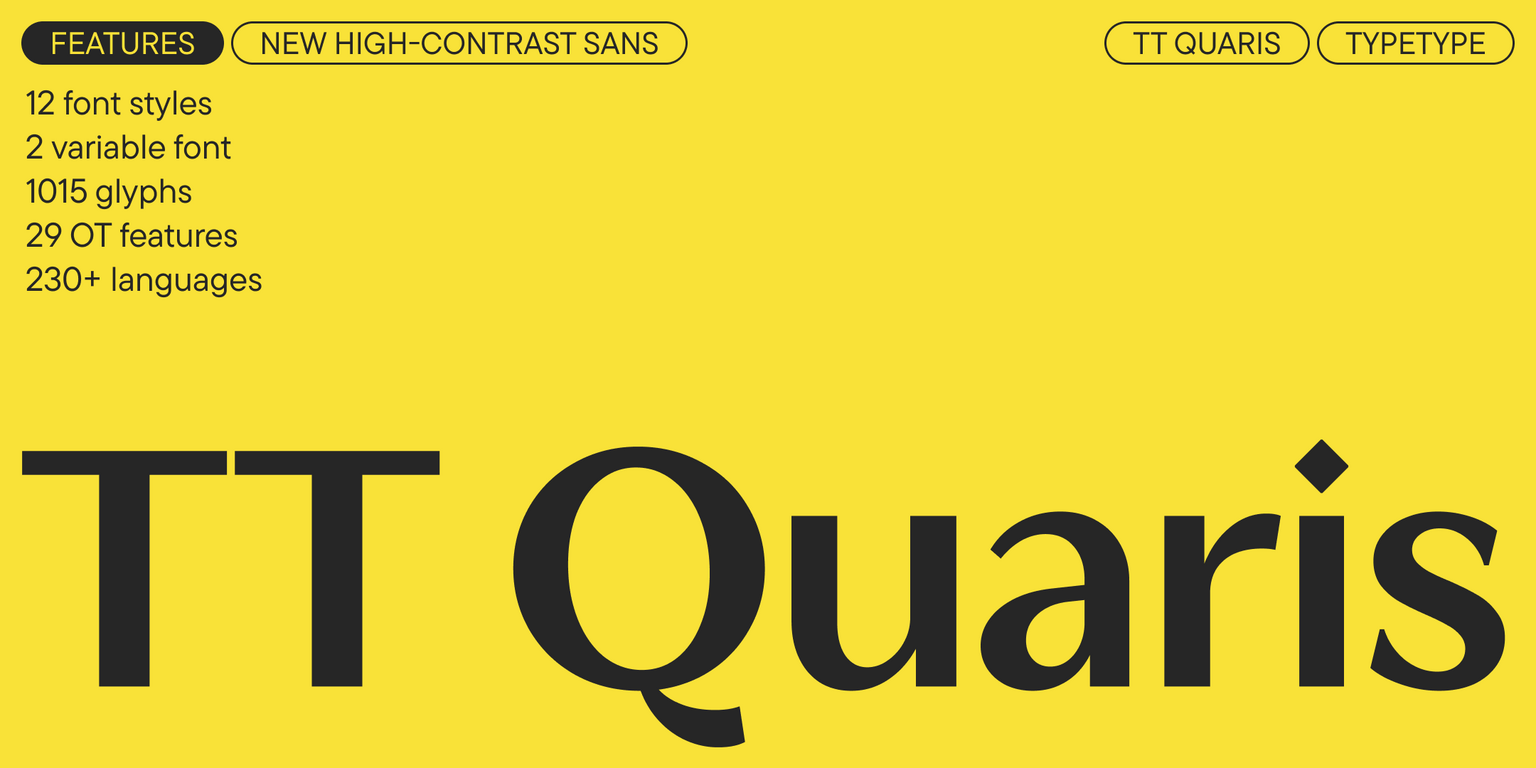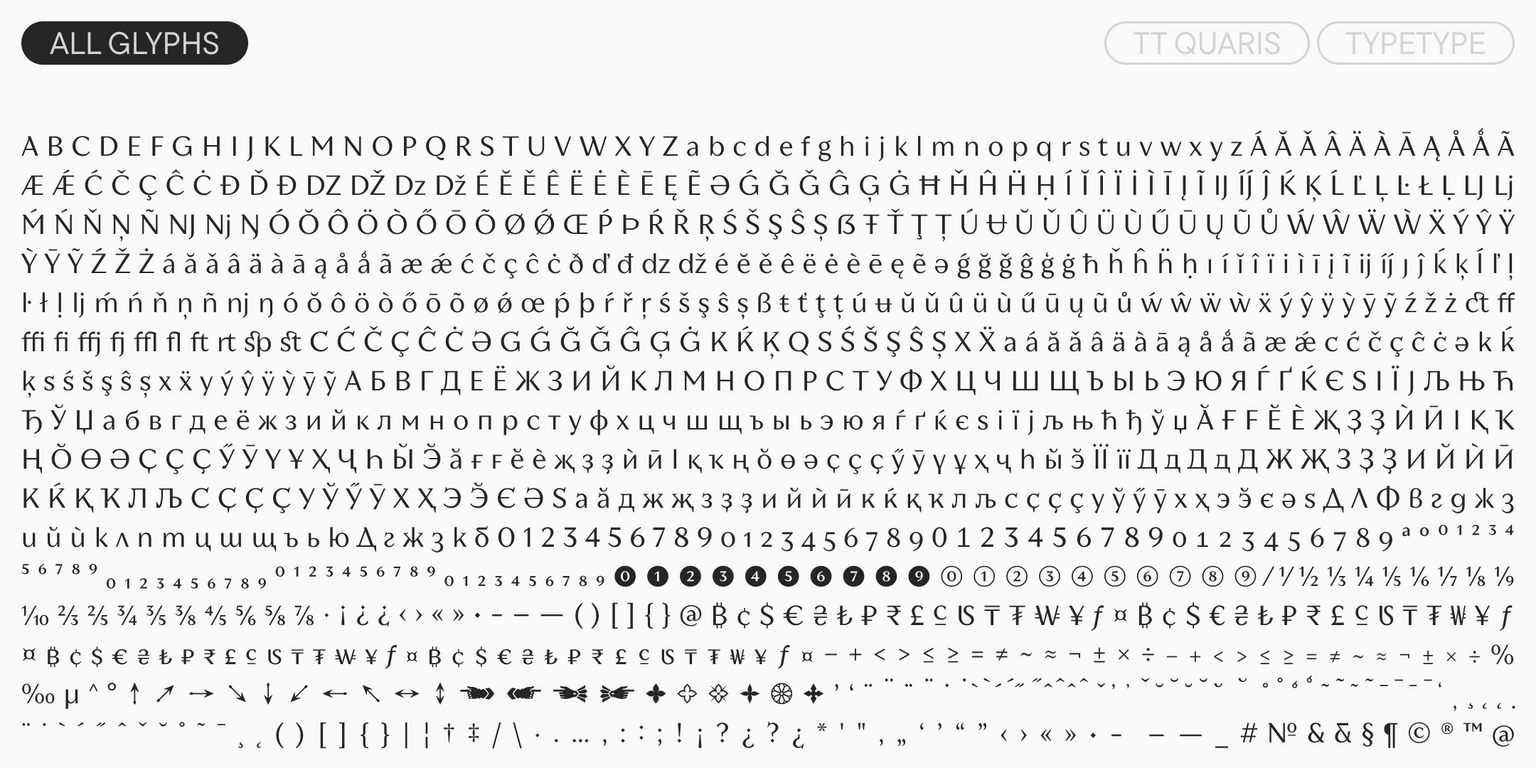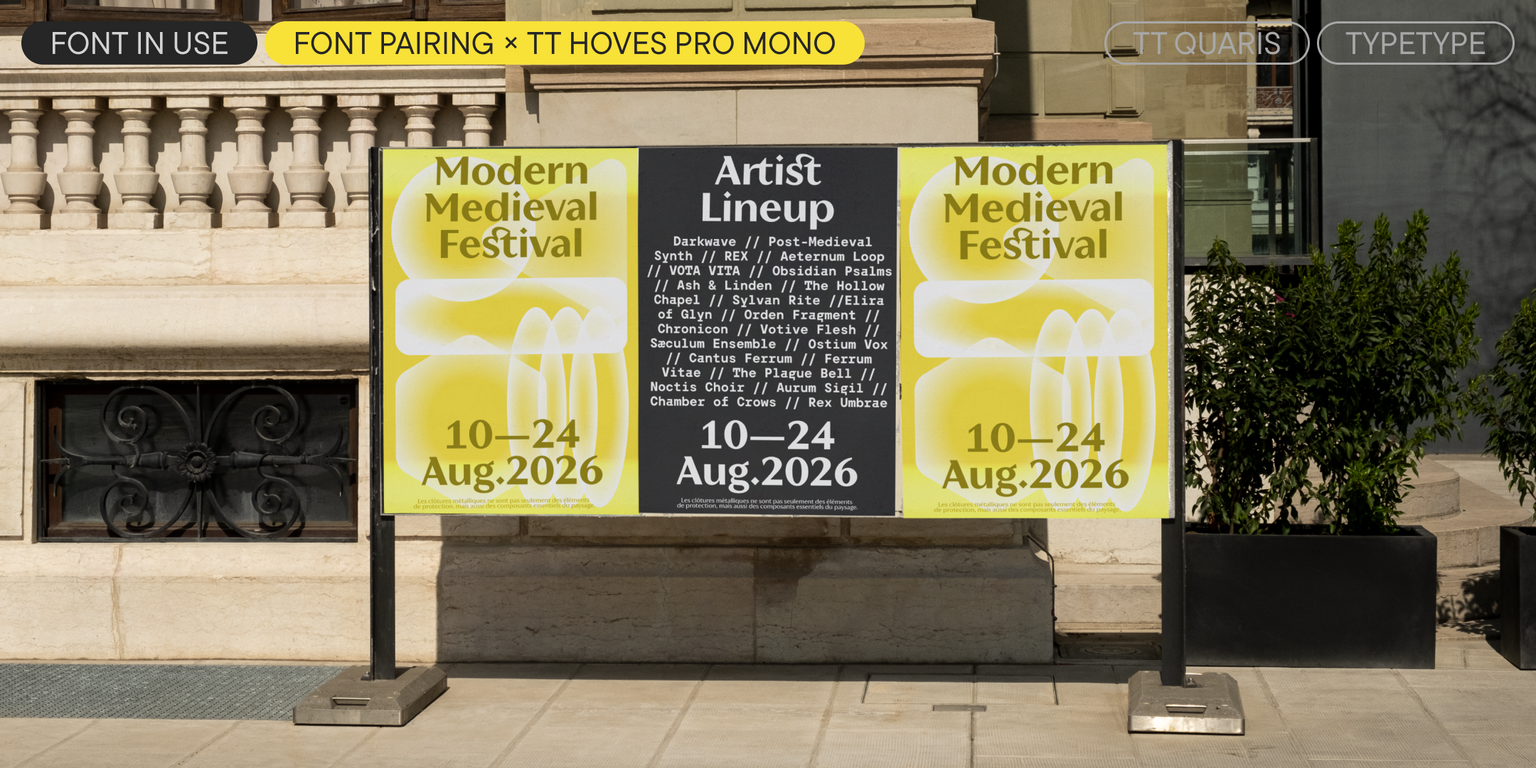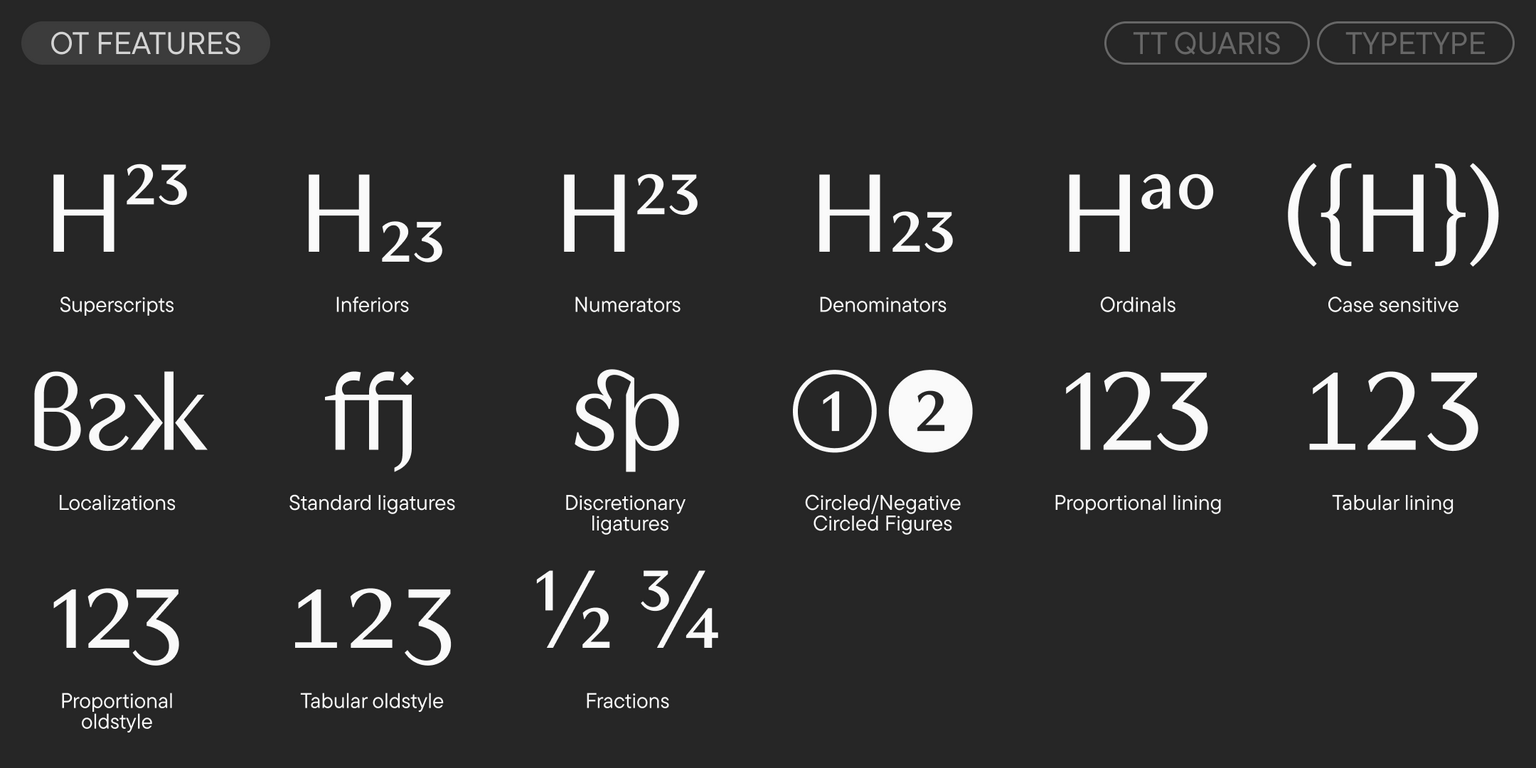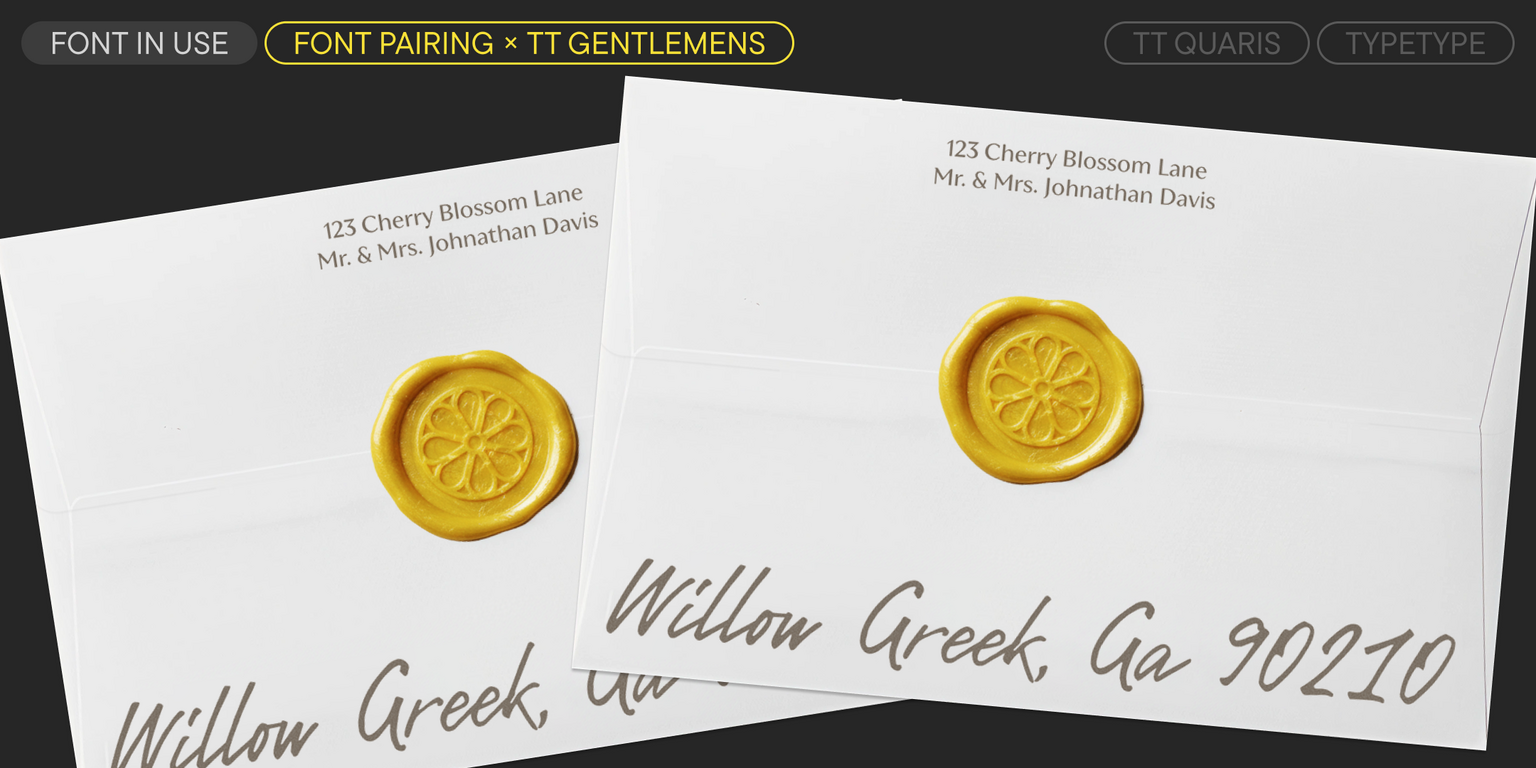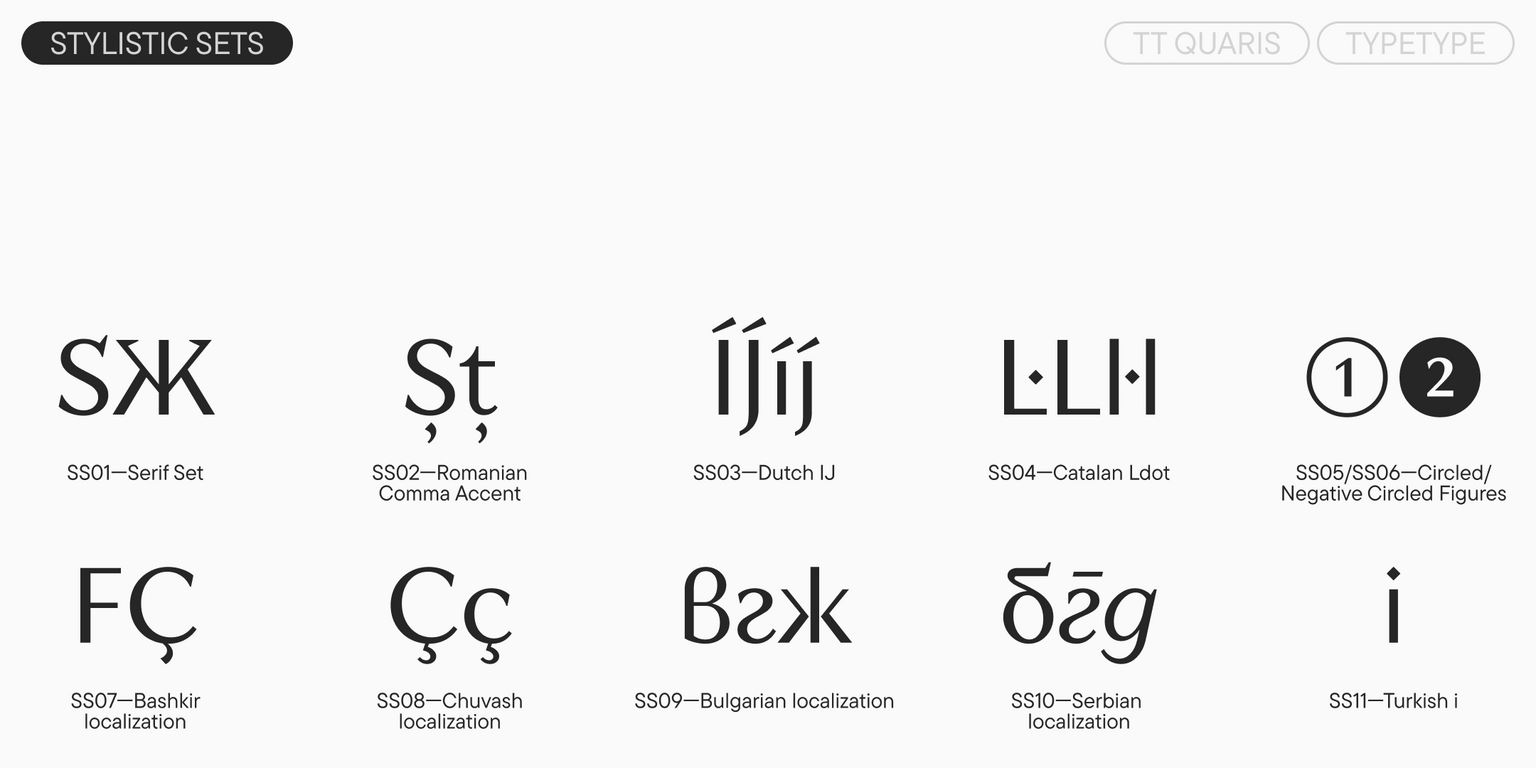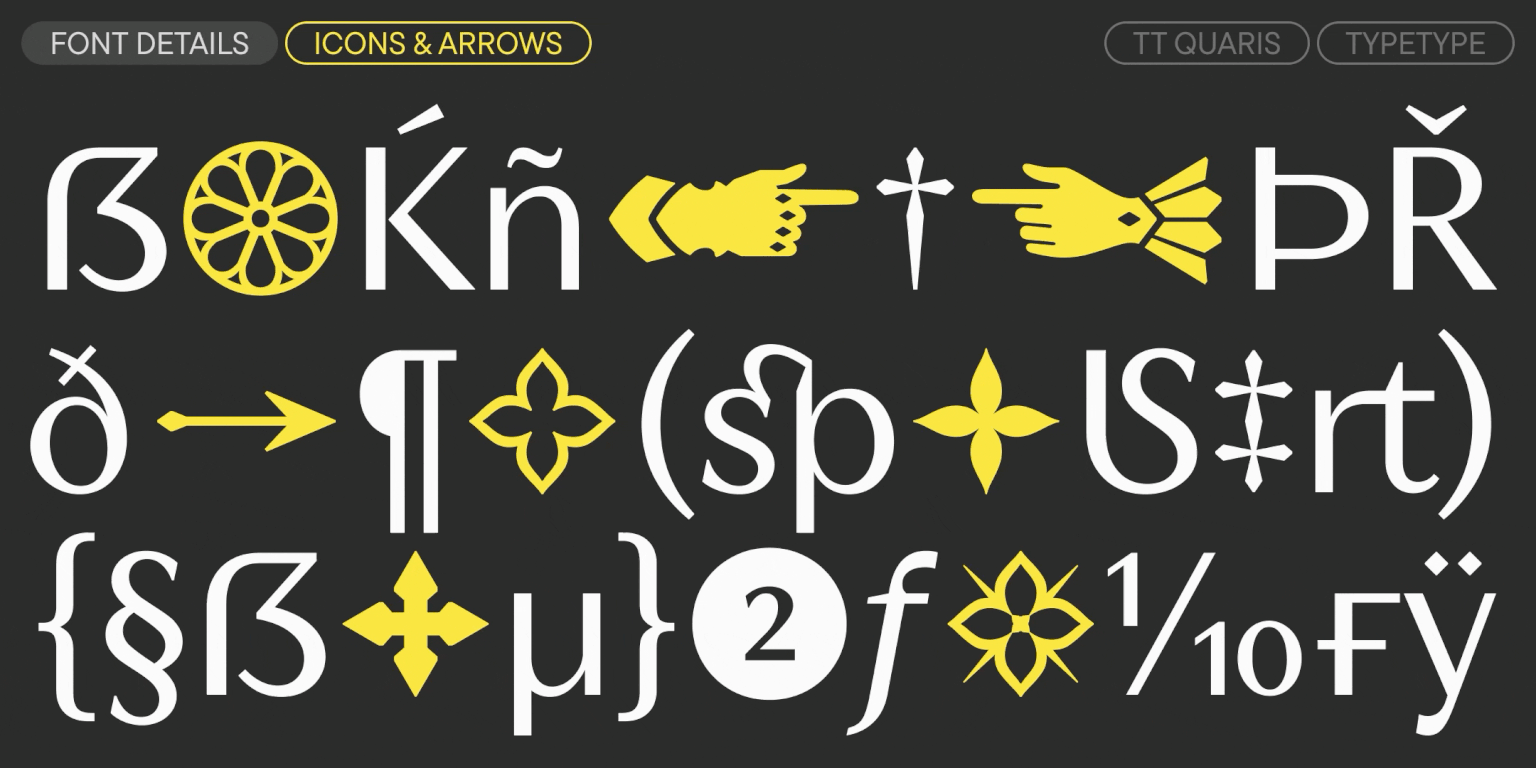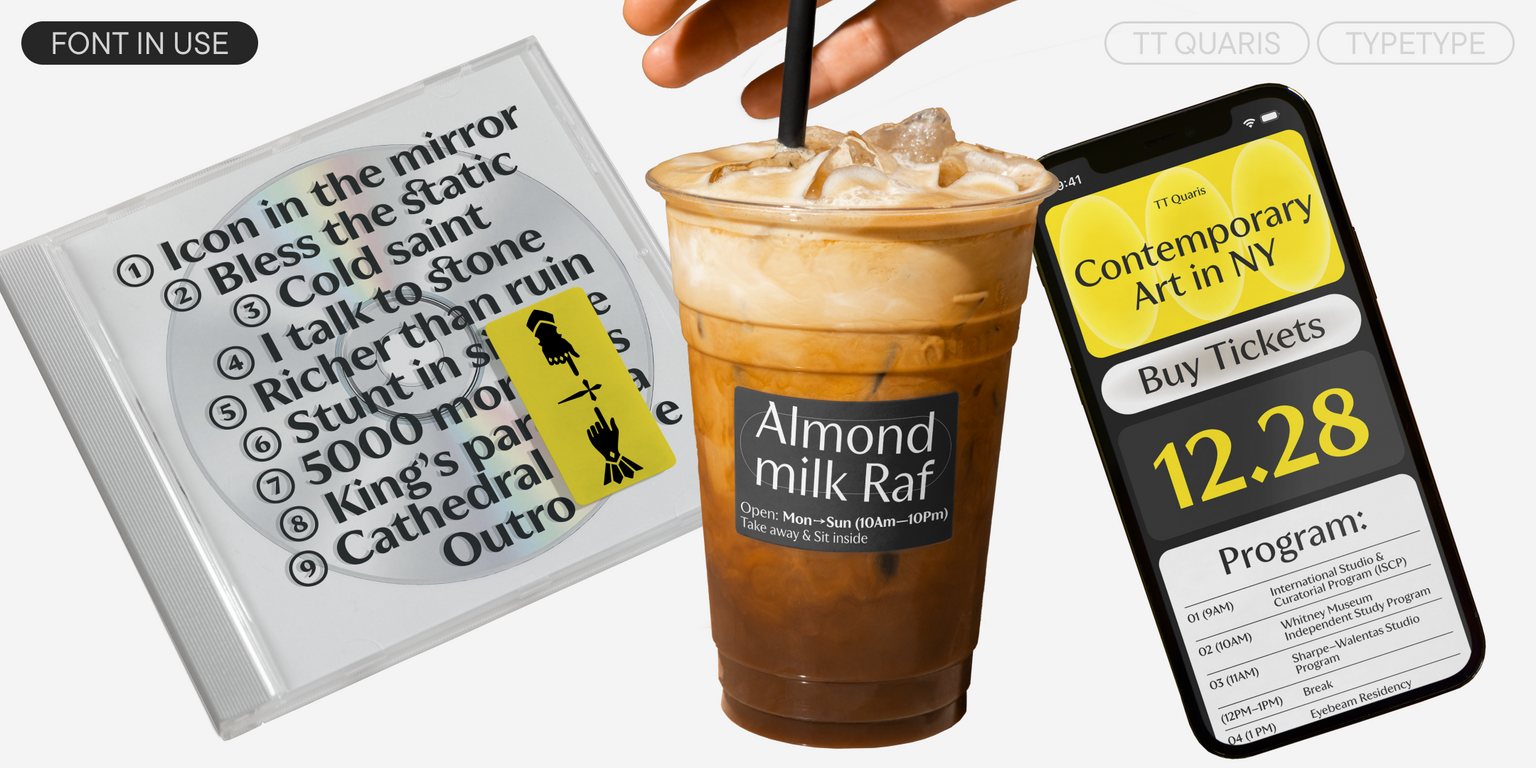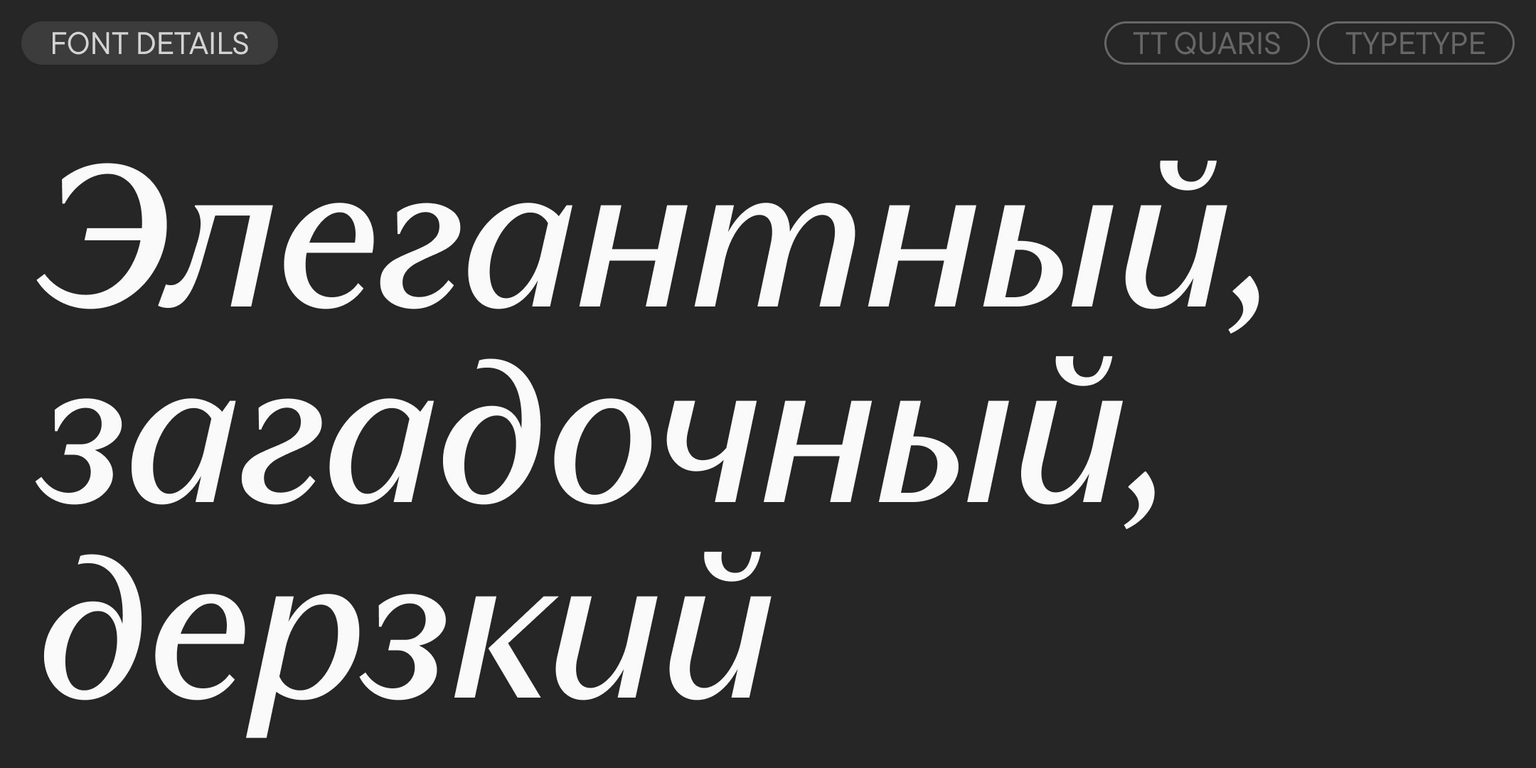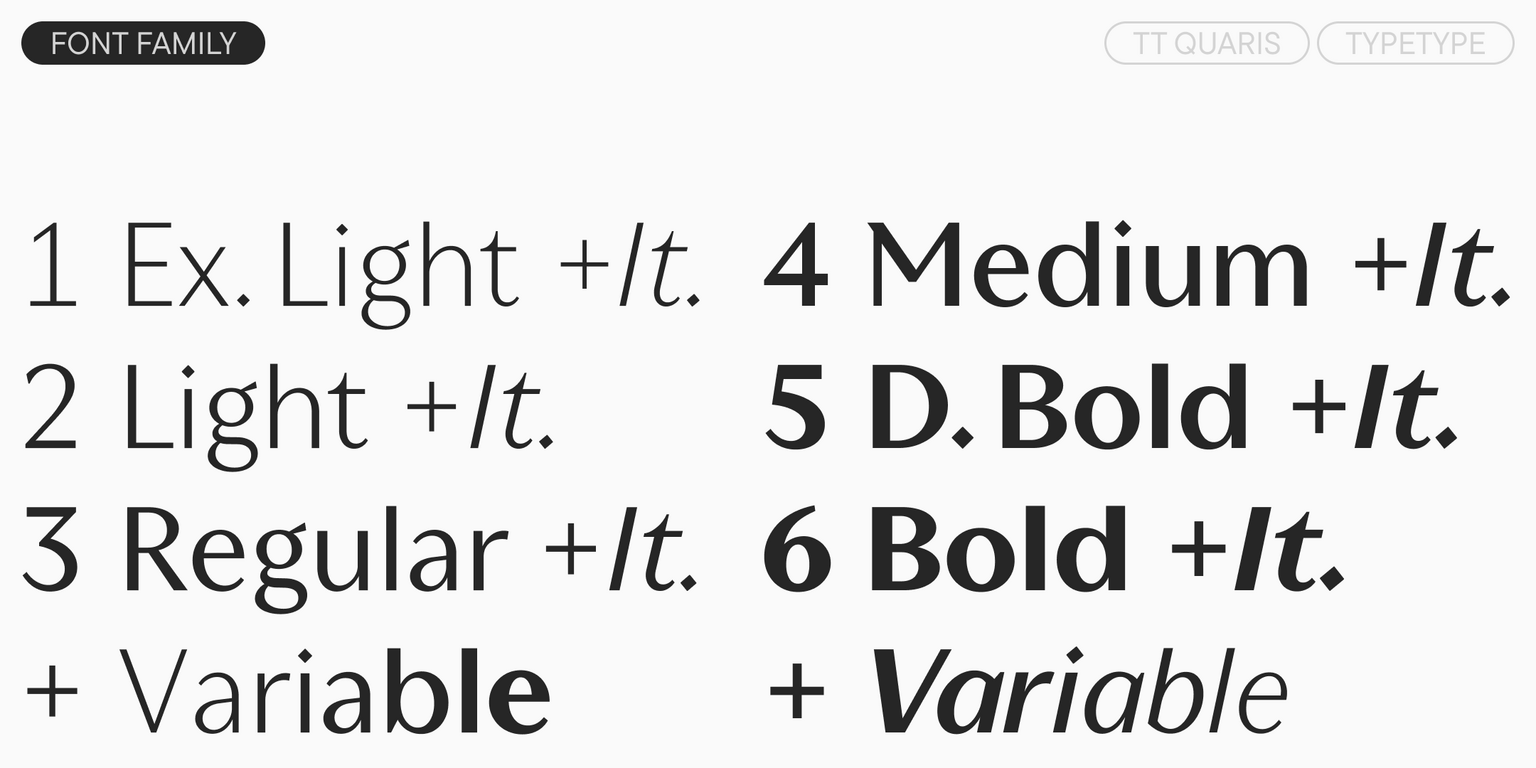
TT Quaris
TT Quaris — ТТ Кварис
Произносится «ТТ Кварис». «Quaris» — искусственно образованное слово от латинского «quartz» (кварц), и своим названием намекает на драгоценные камни. Буквы «TT» являются аббревиатурой названия компании.
TT Quaris — изысканная современная ленточная антиква, рисунок которой балансирует между мягким и колким. Формы знаков в шрифте плавные и стремятся к округлости, однако есть и острые элементы.
TT Quaris
TT Quaris — изысканная и современнная ленточная антиква
TT Quaris
Перед созданием гарнитуры TT Quaris мы провели глубокое исследование архетипов ленточных антикв, чтобы понять их разновидности и определить направление нашей работы. На основе этого исследования были сформулированы основные параметры и стилистические особенности будущего шрифта, после чего мы приступили к его разработке. На создание этого шрифтового семейства ушло более двух лет и 2500 часов кропотливой работы. В результате получился дисплейный и современный, но при этом изящный шрифт. Ключевой особенностью TT Quaris является наличие «колючего стилистического набора» SS01 — Serif Set, доступного через меню OpenType в большинстве графических программ. Этот набор кардинально меняет характер шрифта: из утончённого и благородного он превращает шрифт в дерзкий и вызывающий благодаря появлению острых шпор и шипов в буквах. Ленточные антиквы традиционно находят применение в таких областях дизайна как: оформление ювелирных брендов, косметики и парфюмерии, художественных выставок в музеях, глянцевых изданий, а также в работе различных культурных институций и гастрономических заведений.
TT Quaris это 14 начертаний: 6 прямых, 6 курсивных и 2 вариативных шрифта
Роскошь — внешнее проявление великолепия
Идеальные шрифтовые пары с TT Quaris
Главное правило, которому стоит следовать при создании шрифтовой пары — между двумя шрифтами должны четко прослеживаться как сходства, так и различия. Единство шрифтов можно подчеркнуть следующими характеристиками: контраст, пропорции, ширина, открытость знаков, формы отдельных букв и общий характер. Не бойтесь экспериментировать и пробовать разные сочетания. Анализируйте проекты, которые вам понравилиcь — так вы можете расширить свой визуальный опыт, повысить уровень знаний и уверенности при работе с типографикой.
О гарнитуре TT Quaris
Встречайте новый шрифт в коллекции TypeType — роскошный TT Quaris, в котором объединились элегантность, загадочность и дерзость.
TT Quaris — изысканная и современная ленточная антиква. Перед разработкой этой гарнитуры мы провели глубокое исследование архетипов ленточных антикв. На основе выводов сформулировали основные параметры и стилистические особенности будущего шрифта, после чего приступили к его разработке. На создание семейства ушло более двух лет и 2500 часов кропотливой работы. В результате получился изящный, при этом свежий и небанальный шрифт. В его рисунке есть современные элементы: отсутствие расширений стемов, высокий контраст, стремление к статичности.
TT Quaris — это баланс мягкого и колкого. Название отсылает к гладким драгоценным камням, которым можно придать остроту при огранке. Так, формы знаков плавные и стремятся к округлости, однако есть острые элементы — вершины в «t», геометричные детали, ромбовидные знаки пунктуации. Ключевая особенность гарнитуры — «колючий» стилистический сет с острыми шпорами и шипами в буквах. С его помощью можно кардинально изменить характер шрифта, превратив его из утончённого и благородного в дерзкий и вызывающий.
Особое внимание мы уделили италикам, добавив формы настоящего курсива, которые особенно ярко проявляются в кириллическом наборе. Курсивные начертания немного светлее и заметно уже прямых: такой подход отсылает к классическим италикам, однако в TT Quaris они выглядят актуально и современно.
Возможности работы с гарнитурой расширяют два вариативных шрифта (прямой и курсивный), меняющихся по оси жирности. Также дизайн поможет дополнить сет иконок, связанный со средневековой темой рыцарства и романтизма: среди них вы найдёте узоры из орнаментов и витражи готических соборов.
TT Quaris отлично впишется в айдентику ювелирного бренда, может использоваться на упаковках косметики и парфюмерии, будет гармонично смотреться в оформлении выставок и навигации в музеях, на обложках глянцевых изданий, в меню баров и ресторанов.
TT Quaris — это:
• 14 начертаний: 6 прямых, 6 курсивных и 2 вариативных шрифта;
• 1015 знаков в прямых начертаниях и 1003 знака в италиках;
• 29 OpenType фич;
• Поддержка 230+ языков.
TT Quaris — настоящий бриллиант в мире антикв!
ss01 | Serif Set